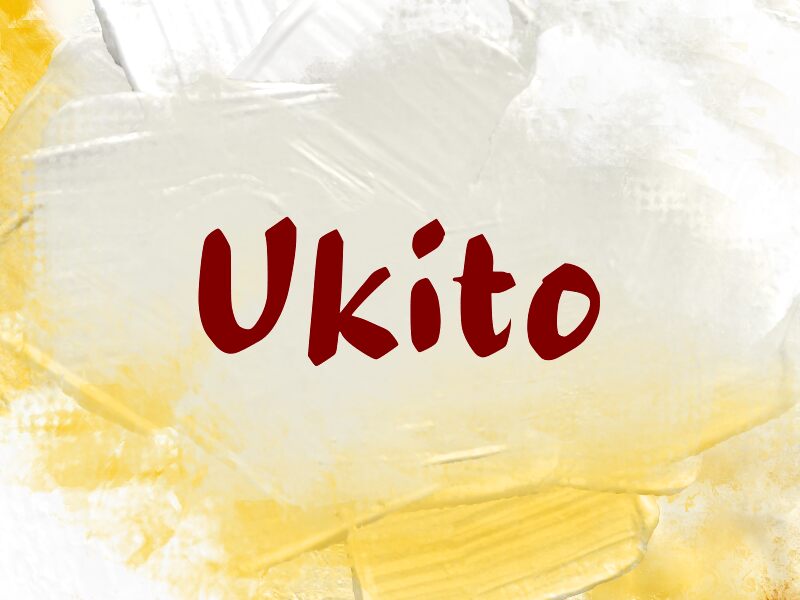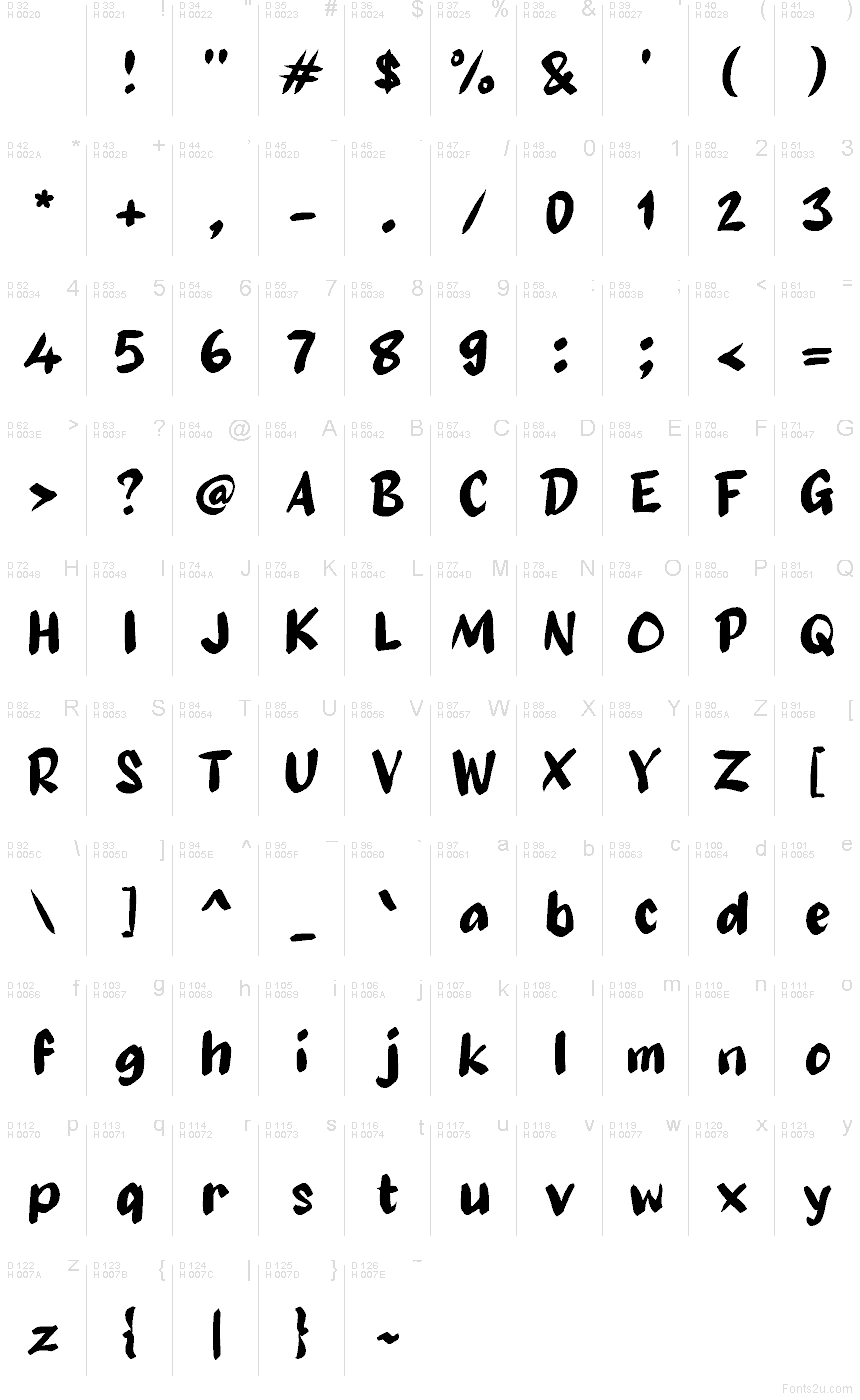
Ukito, créé par Wep, est une police pinceau gratuite au rythme brut, chargée d'encre, avec un côté résolument urbain. Ses lettres semblent tracées d'un trait de pinceau généreux : des pleins marqués, des jointures serrées et des bords irréguliers qui donnent au logotype une impulsion vive et artisanale, sans jamais paraître brouillonne.
Elle est idéale pour les affiches, les visuels musicaux, l'image de marque de cafés, le packaging ou les titres qui nécessitent cette énergie picturale épaisse. En tant que police gratuite, Ukito est aussi très efficace pour les textes de couverture, les en-têtes de réseaux sociaux et les grandes citations, car ses lettres compactes et denses conservent tout leur impact, même sur les mots courts.
Ukito
Présentation et spécimen de la police Ukito